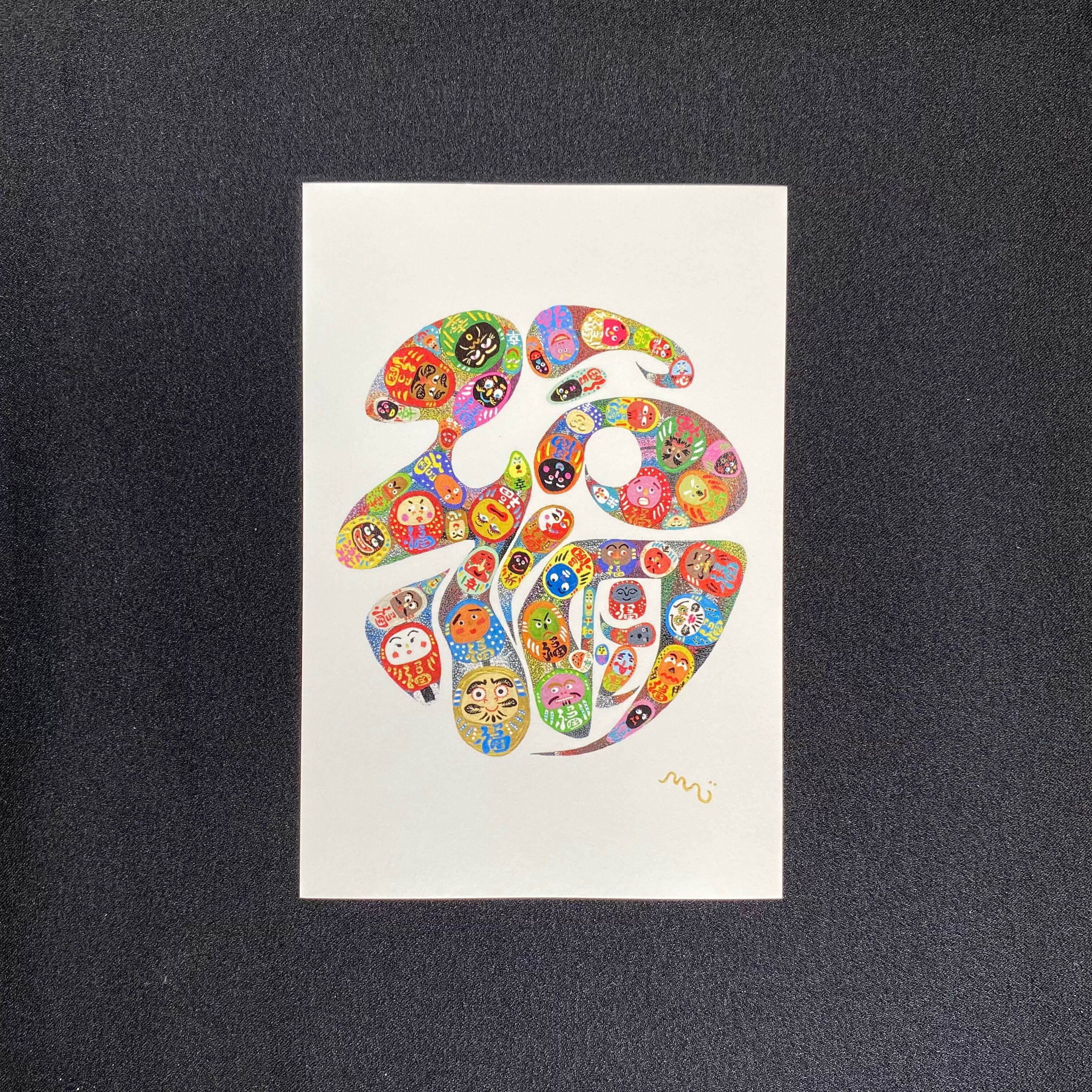
『縁起福だるま』~ふつうのこと〜
『縁起福だるま』
福の文字の中に、肌の色や性別、大きさや形、様々な表情のだるまを描くことで、本来の「福」の意味や世界の平和を願う気持ちを込めた作品。
『福』~ふつうのこと~
夢や目標を抱くことは大切なこと。
想いが強すぎると「重い」になってしまい身動きがとれなくなります。
普段通りの暮らしがおくれることは「運がいい」こと。
それに気がつくと「幸福」になります。
何か特別なことではなく、何も起きないことがどれほど幸せであるか。
毎日がただ淡々と過ぎていくことが、「幸せの本質」かもしれません。